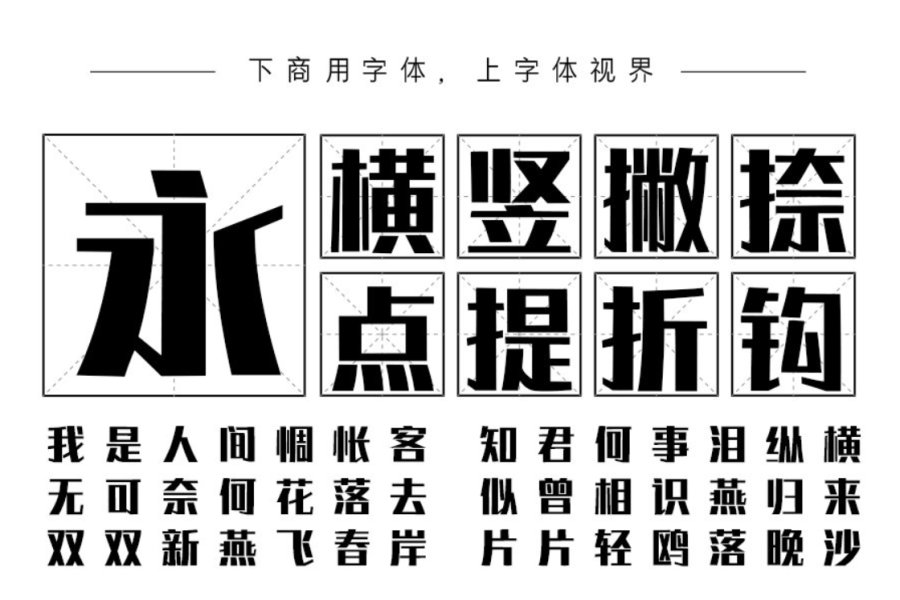
阿里汉仪智能黑体:这是一款AI字体产品,汉智能黑体基于黑体的横竖基本特征,加大横竖粗细比例,字面饱满填充整个内框,让字体更加醒目,视觉冲击力极强,能够很好的与用户对话,非常适用于电商类广告设计。
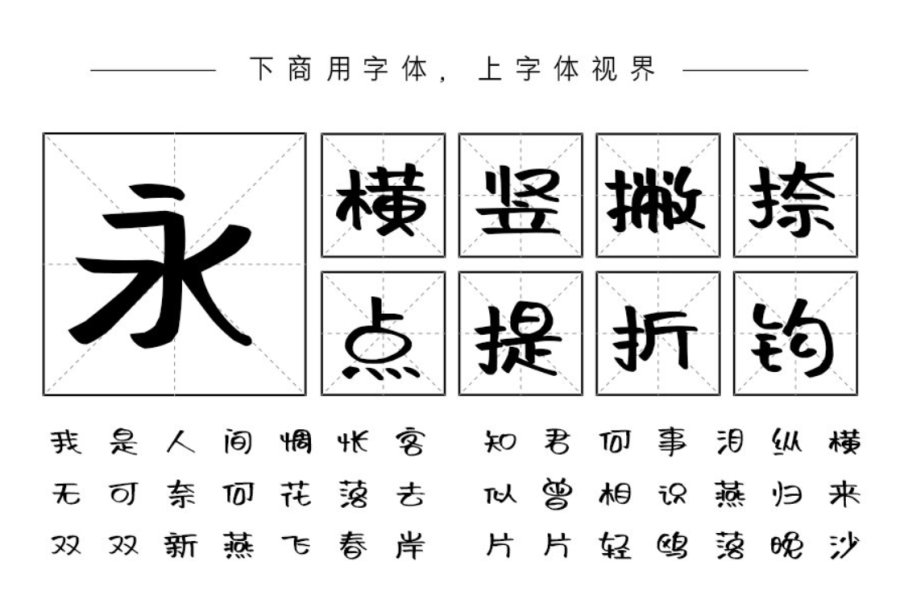
阿朱泡泡体:这一款字体书写笔画随意放松,富于变化,充满卡通趣味极富装饰色彩,特别是口型偏旁由泡泡组成,使字体充满青春活力风格鲜明,特点突出,能够适用于艺术设计、包装印刷、签名设计、图形设计等领域。
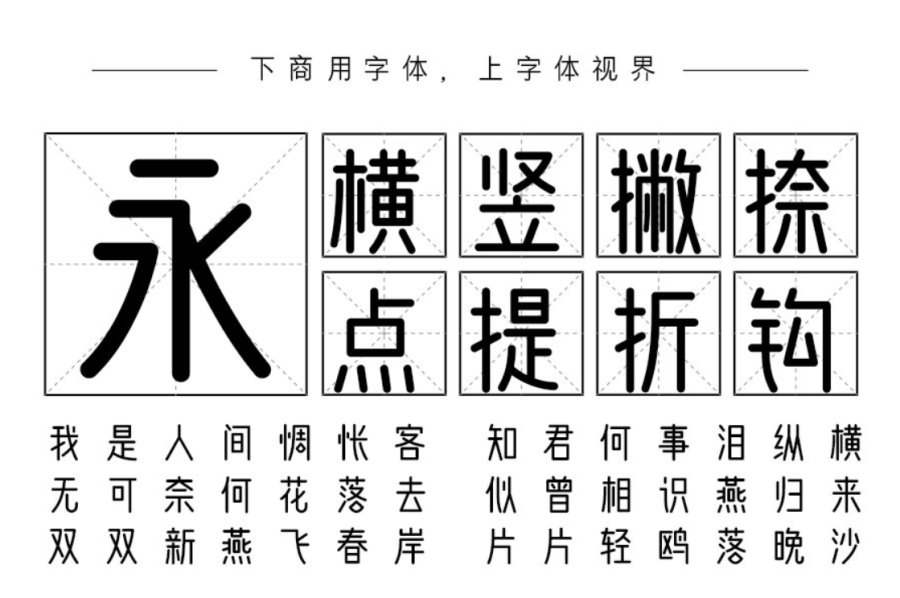
问藏书房:从问藏书房字体图片可以看出的设计整体现代简约,中宫紧凑,视觉阅读极具层次感,字字俊秀且呈现古雅之风,设计团队以精心的设计赋予了汉字全新美感!